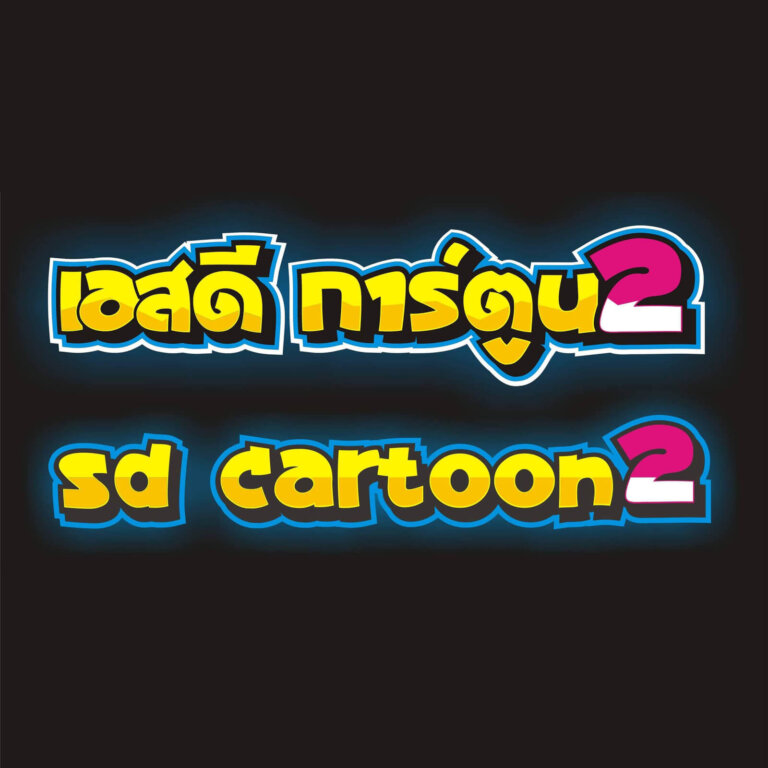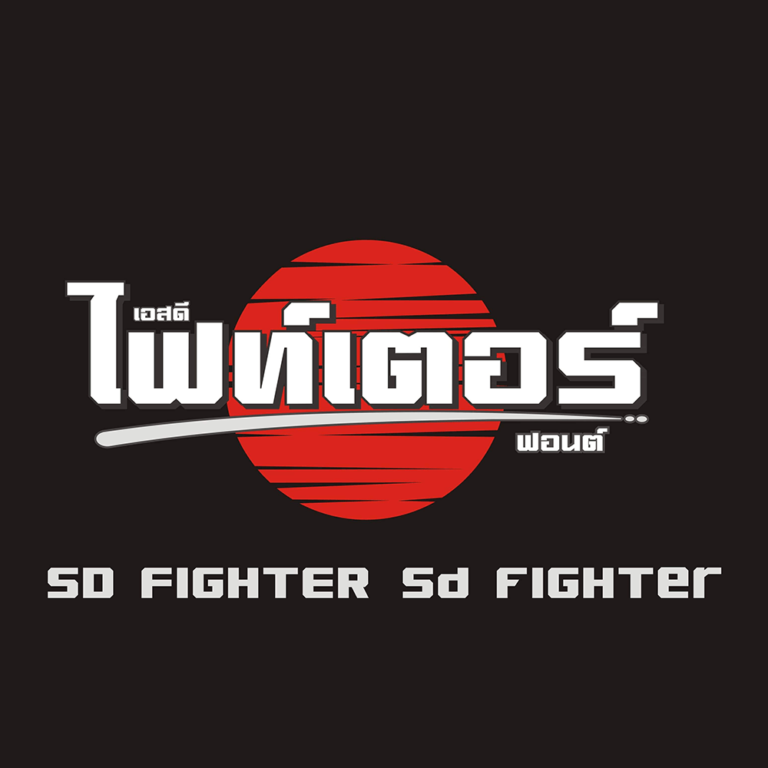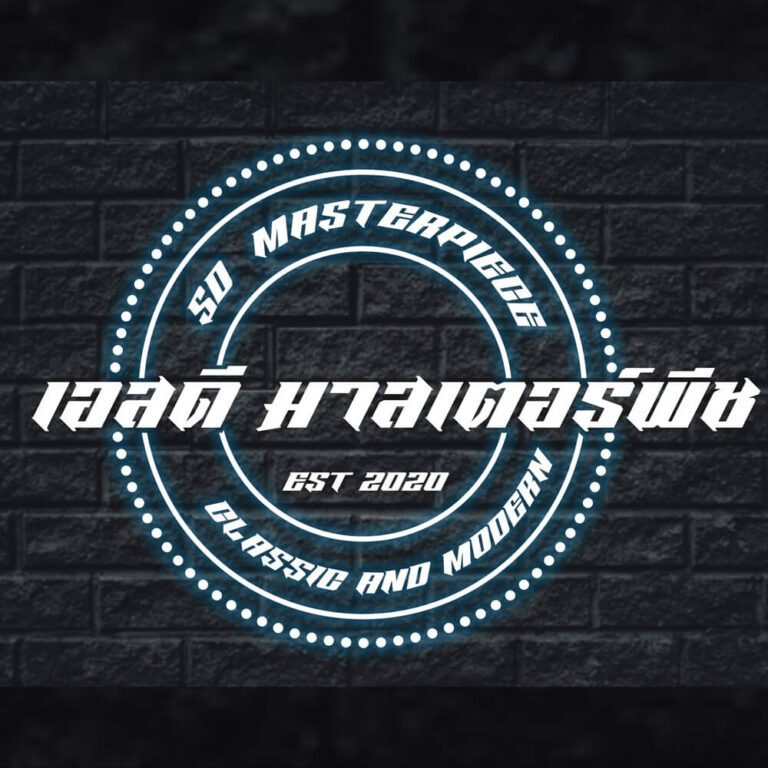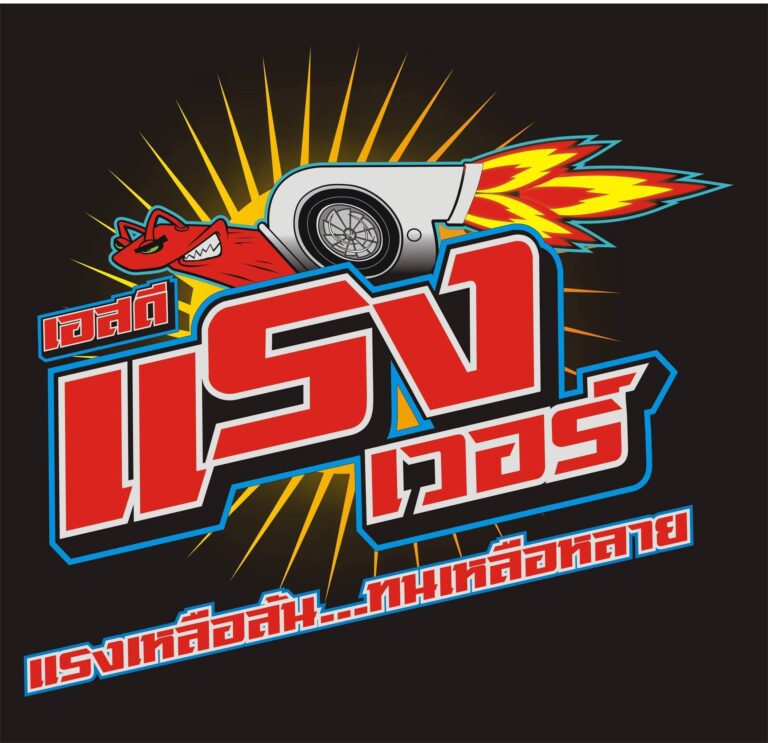
สร้างสรรค์ฟอนต์ไว้ทั้งหมด 17 ตัว
เอสดี โปรโตไทป์ (sd prototype)
เอสดี โปรโตไทป์ เป็นฟอนต์ออกแนวกึ่งทางการ เหมาะสำหรับพาดหัวต่างๆ ทำไว้นานแล้วตอนช่วงโควิดระบาด  ไม่ได้ไปไหนเลยขึ้นแบบลายเส้นไว้ พึ่งจะนำมาแปลงเป็นไฟล์ ttf นำมาแจกให้ทุกท่านได้ใช้งานกัน หลังจากนี้จะเอาฟอนต์ที่ทำสะสมไว้มาแจกต่อเรื่อยๆ ครับ
เอสดี เรซโซน2 (sd racezone2)
เอสดี เรซโซน2 เป็นฟอนต์ที่ได้แนวคิดมาจาก font SWIPE RACE ของ CKdesign โดยรูปแบบตัวอักษรทุกตัวทั้งภาษาไทย ตัวเลข และภาษาอังกฤษ จะมีเอกลักษณ์คือมีลักษณะปลายแหลมด้านซ้ายของตัวอักษรทุกตัว ออกแนวซิ่ง สปอร์ตตามเคย
เอสดีนิวนอร์มอล (sd newnormal)
เอสดีนิวนอร์มอล เป็นฟอนต์ที่ทำไว้ในช่วง โควิด-19 ระบาดรอบแรก ช่วงนั้นปิดร้านไปหลายวัน เลยนั่งทำฟอนต์นี้ขึ้นมา เป็นฟอนต์แนวทางการอ่านง่ายๆ สบายตา เหมาะสำหรับทำป้ายบ่งบอกสถานที่ต่างๆ
เอสดีโปรเทคเตอร์ (sd protector)
เอสดีโปรเทคเตอร์ เป็นฟอนต์ที่ได้แนวคิด มาจาก ฟอนต์ KZ Excel ทำการดัดแปลงมุมความแหลมของตัวอักษรให้เหลือ 30 องศา ของเดิมน่าจะประมาณ 60 องศา ทั้งส่วนหัวด้านบน และด้านล่าง ของตัวอักษรปรับเปลี่ยนใหม่ให้ดูเหลี่ยมขึ้น นำมาให้เพื่อนๆ ร้านป้ายและสายกราฟิกได้ใช้กันเช่นเคย
เอสดี โซคิ้วท์ (SD SOCUTE)
เอสดีโซคิ้วท์ เป็นฟอนต์แนวการ์ตูนอีกสักฟอนต์ ปกติไม่ค่อยได้ทำฟอนต์แนวนี้สักเท่าไหร่ นานๆ ทำที มั่วเข้าป่าไปเรื่อย ฟอนต์นี้ ทำไว้ 2 เวอร์ชัน ปรับเปลี่ยน ตัวอักษร แค่ ข ฃ จ ฐ ธ แล้วแต่คนชอบ
เอสดี มาสเตอร์พีซ (sd masterpiece)
เอสดี มาสเตอร์พีซ เป็นฟอนต์ออกแนว Modern Classic ผสมผสานแนว Vintage ตอนแรกตั้งใจจะทำเฉพาะ ภาษาอังกฤษเช่นเดียวกับ sd best in class แต่ทำไปทำมาเลยเติมภาษาไทยมาด้วย เผื่อมีคนชอบแนววินเทจบ้าง
เอสดี แรงเวอร์ (sd rangver)
ฟอนต์ เอสดี แรงเวอร์ เป็นฟอนต์ที่ได้แรงบันดาลใจจาก เครื่องดื่ม แรงเวอร์ พอดีเดินเข้าไปในร้านสะดวกชื้อเห็นมีเครื่องดื่มหลายชนิด แต่ไปสะดุดตรงยี่ห้อพอดี เลยนำมาต่อยอดเป็นตัวอักษรทั้ง 44 ตัว ทำเป็นฉบับเต็มขึ้นมา  นำมาแบ่งปันให้เพื่อนๆ ในสายงานกราฟิก ห้างร้าน บริษัท องค์กร และหน่วยงานอื่นๆ ที่ต้องการนำตัวหนังสือไปใช้ในการสร้างสรรค์ผลงานของตัวเองได้ใช้กัน
เอสดี ไฟท์เตอร์ (sd fighter)
เอสดี ไฟท์เตอร์ เป็นฟอนต์ที่ได้แรงบันดาลใจจากโฆษณารถโตโยต้า รีโว ซึ่งมีข้อความ “ตัวตนของฅนจริง” เลยอยากจะทำเป็นฟอนต์ขึ้นมา รูปร่างฟอนต์ ออกแนวเหลี่ยมๆ ดูแข็งแกร่งมีพลังดี นำมาให้เพื่อนๆ สายงานกราฟิก และหน่วยงานอื่นๆ ได้ใช้กัน
เอสดี การ์ตูน2 (sd cartoon 2)
เอสดี การ์ตูน2 เป็นฟอนต์ที่ต่อจาก เอสดีคอมมิค หลังจากที่ทำฟอนต์แนวซิ่งๆ มาแจกหลายฟอนต์แล้ว ฟอนต์นี้ออกแนวตัวมน กลมๆๆๆ ดองไว้นานมากฟอนต์นี้ นำมาให้เพื่อนๆ ในสายงานกราฟิก และหน่วยงานอื่นๆ ได้ใช้กัน
เอสดี คลิงออนเบลด2
เป็นฟอนต์ที่ต่อจากเวอร์ชัน 1 ที่มีแต่ภาษาไทย มาเพิ่มเติมภาษาอังกฤษตอนหลังและปรับเปลี่ยนตัวอักษรภาษาไทยบางตัว นำมาให้เพื่อนๆทุกท่านทั้งสายงานกราฟิก และสายอื่นๆ นำไปใช้กัน
เอสดี เพอร์ฟอร์แมนซ์ (SD Performance)
เป็นฟอนต์แนวซิ่งๆๆ เหมือนเดิมครับ เหมาะสำหรับยุคที่การแต่งรถด้วยสติ๊กเกอร์กำลังเป็นที่นิยมในกลุ่มวัยรุ่น
SD Best in Class
เอสดี โชคดี (sd chokdee)
เอสดี โปรสตรีท (sd prostreet)
sd hall
หลังจากที่มีโอกาสได้ปล่อยฟอนต์ตัวแรกไปแล้ว ฟอนต์นี้เป็นฟอนต์ที่สองครับมีชื่อว่า เอสดี ฮอลล์ ได้แนวคิดมาจากลูกอมฮอลล์